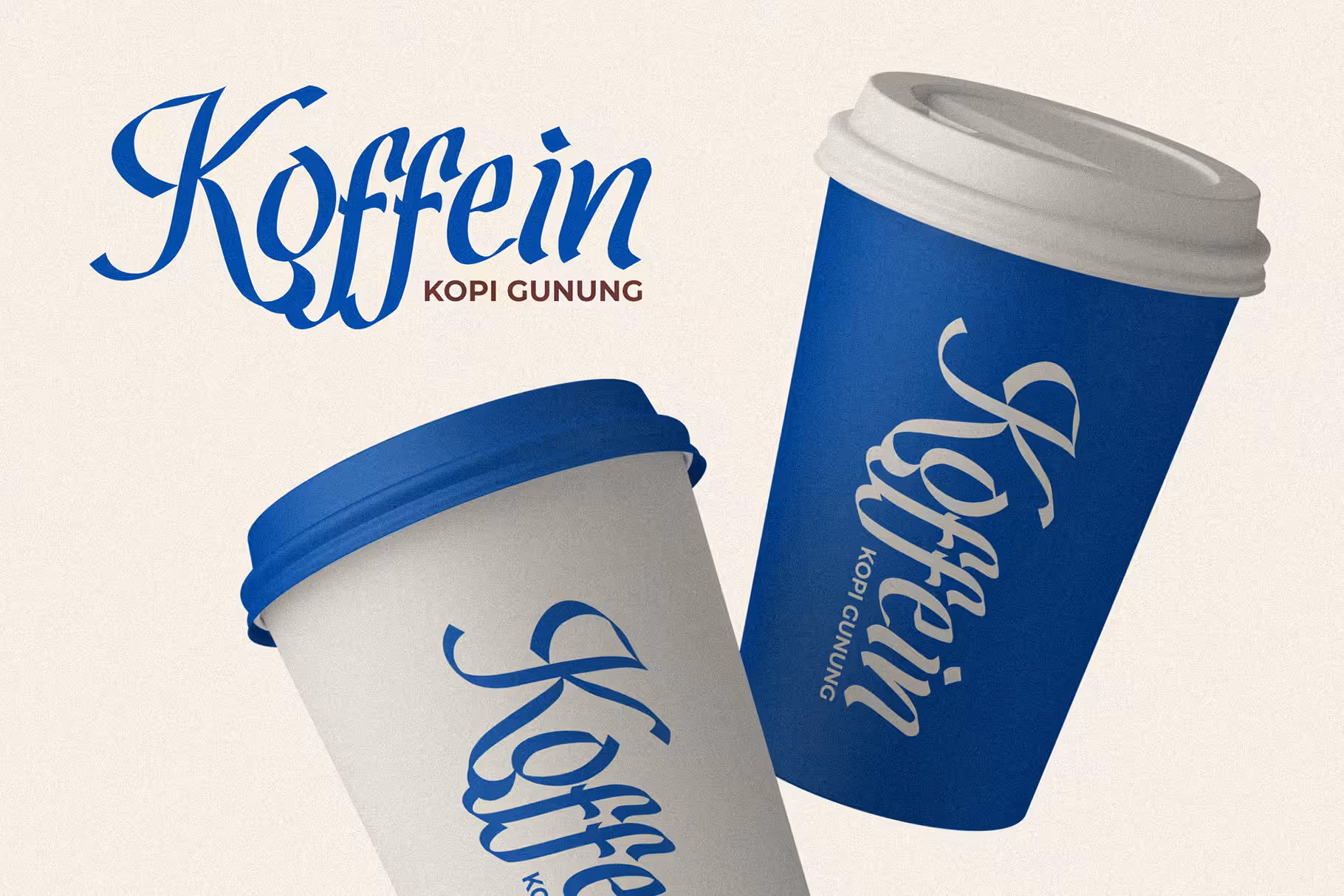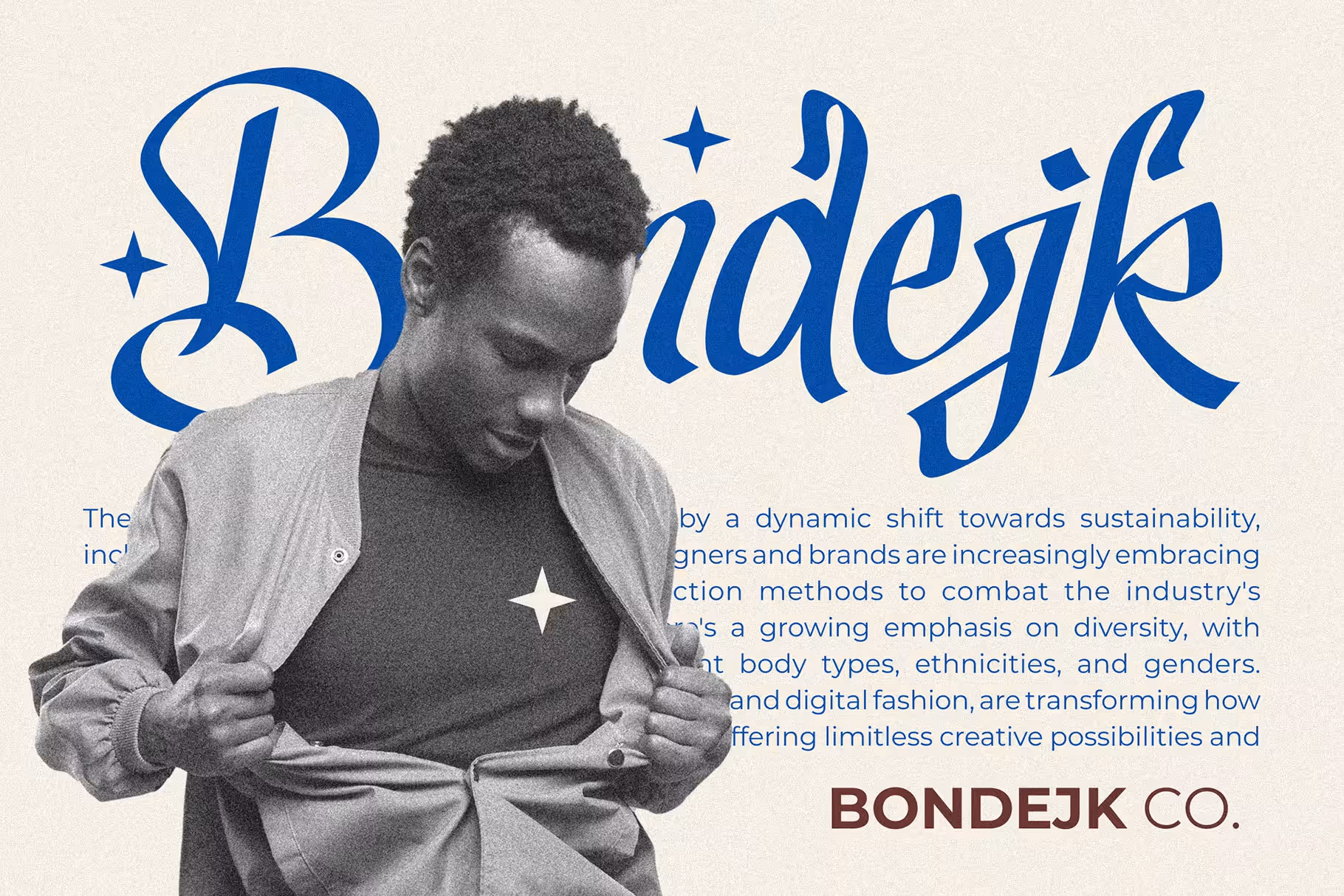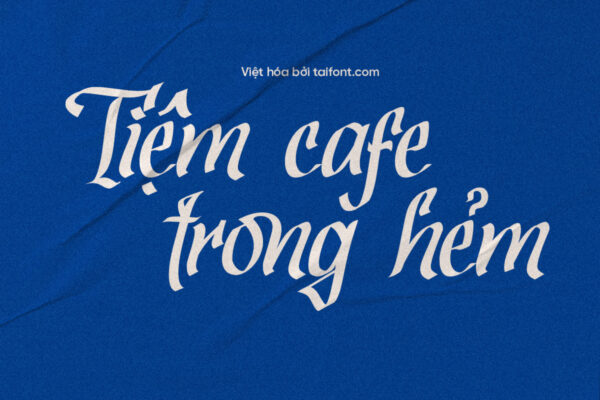
Giới thiệu về Font TF Rudgion Script Việt hóa
TF Rudgion Script Việt hóa là một font chữ viết tay (script font) nổi bật với thiết kế vintage, mềm mại và đầy duyên dáng, lý tưởng để tạo nên sự ấm áp, hoài niệm và một chút lãng mạn cho mọi thiết kế. Font này toát lên phong thái cổ điển, gần gũi và đầy cuốn hút, phù hợp để thu hút mọi ánh nhìn và tạo ấn tượng đặc biệt.
Với sự duyên dáng trong từng đường nét, phong cách vintage đặc trưng và tính thẩm mỹ cao, Rudgion Script là lựa chọn hoàn hảo cho các thiết kế muốn truyền tải sự ngọt ngào, hoài niệm và sự gần gũi, đặc biệt là trong lĩnh vực thiết kế thương hiệu cà phê:
- Thiết kế thương hiệu cà phê: Hoàn hảo để sử dụng cho logo quán cà phê, menu, bao bì cà phê, hoặc các ấn phẩm quảng bá. Nét chữ mềm mại, vintage của font sẽ làm cho thương hiệu trở nên ấm cúng, gần gũi và đầy phong cách, gợi cảm giác về những buổi chiều thư giãn bên ly cà phê.
- Thiết kế phong cách Vintage: Lý tưởng để sử dụng trong các ấn phẩm muốn tái hiện không khí của những năm tháng đã qua, như thiệp mời, bao bì sản phẩm, hoặc các ấn phẩm kỷ niệm. Font này giúp tạo không khí chân thực và gợi cảm xúc về một thời đã xa.
- Thiết kế nhận diện thương hiệu: Phù hợp cho logo hoặc bộ nhận diện thương hiệu muốn truyền tải sự tinh tế, độc đáo và giá trị lâu đời, đặc biệt là các thương hiệu liên quan đến ẩm thực, đồ handmade, hoặc các sản phẩm mang tính di sản.
- Trích dẫn và slogan: Tuyệt vời để tạo các câu trích dẫn đầy cảm hứng, slogan hoặc các dòng chữ cần sự nổi bật và mang tính biểu cảm trên mạng xã hội hoặc các ấn phẩm khác, đặc biệt khi kết hợp với hình ảnh mang hơi hướng cổ điển hoặc nghệ thuật.
Với TF Rudgion Script Việt hóa, bạn có thể dễ dàng thổi hồn vintage, sự tinh tế và vẻ đẹp lãng mạn vào các thiết kế, tạo ra những sản phẩm không chỉ đẹp mắt mà còn đầy cảm xúc và sức hút đặc biệt.